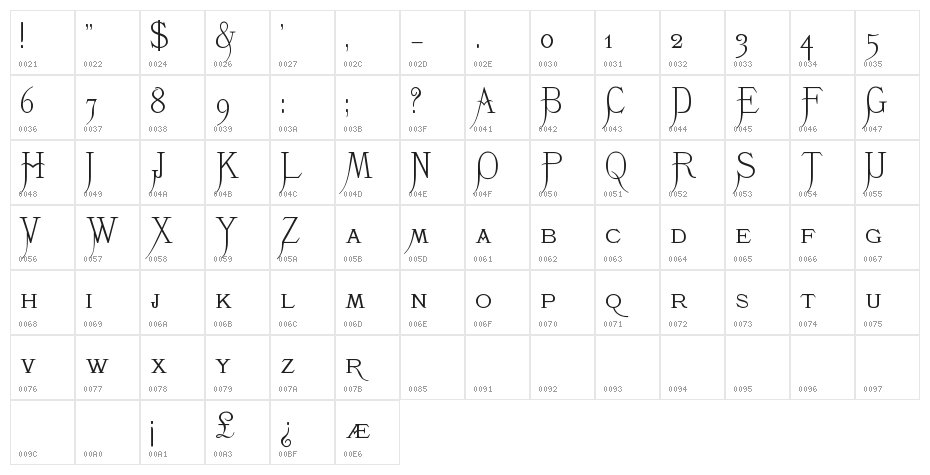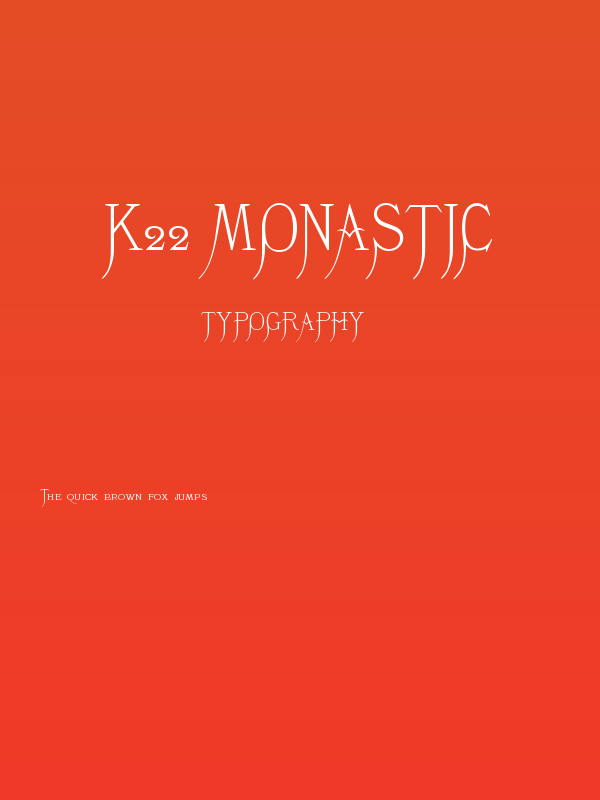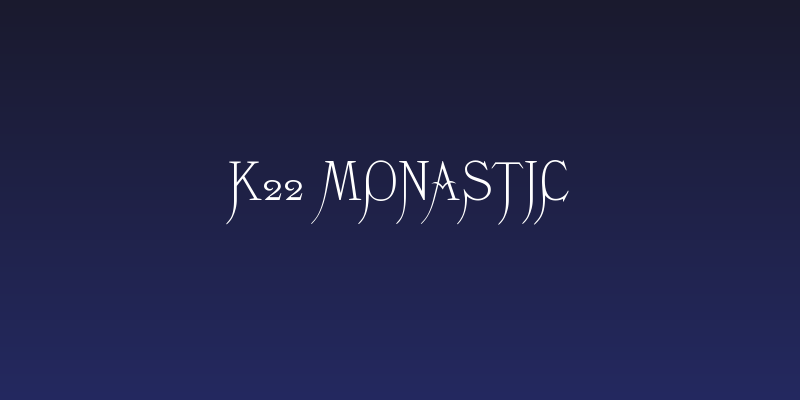
K22 Monastic Font
| Categorie | Gothic |
| Caso d'uso | Headlines, Logos, Decorative text |
| Progetti proposti | Ideal for historical themed designs, book covers, branding for luxury products, and decorative invitations. |